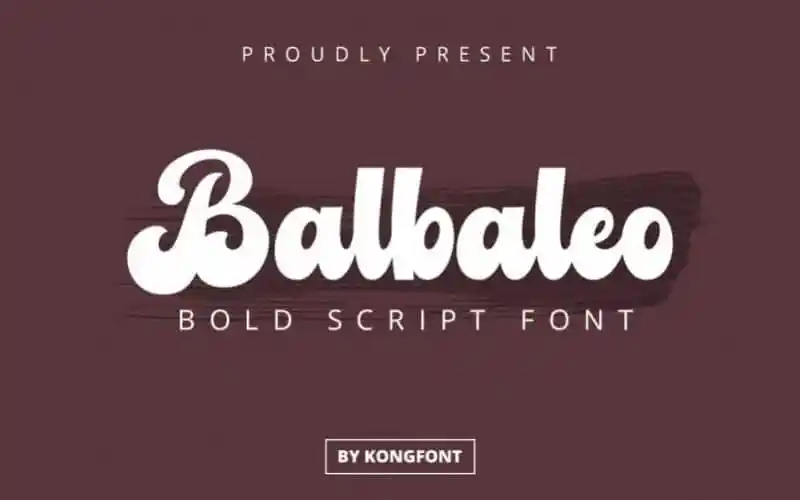
Balbaleo Bold Script Font
A Balbaleo Bold Script Font é uma elegante fonte cíntica escrita a mão, projetada cuidadosamente para atender a uma ampla gama de necessidades digitais. Com base nos designs de fontes elaborados por Kong Font, esta tipografia foi criada através da fusão de estilos modernos e técnicas artesanais. Perfeita para produzir mensagens destacadas em capítulos femininos de romances ou para enfatizar a personalidade feminina, ela também oferece um toque sofisticado que se ajusta perfeitamente a logotipos pessoais, logos de produtos e cartões de convite de casamento.